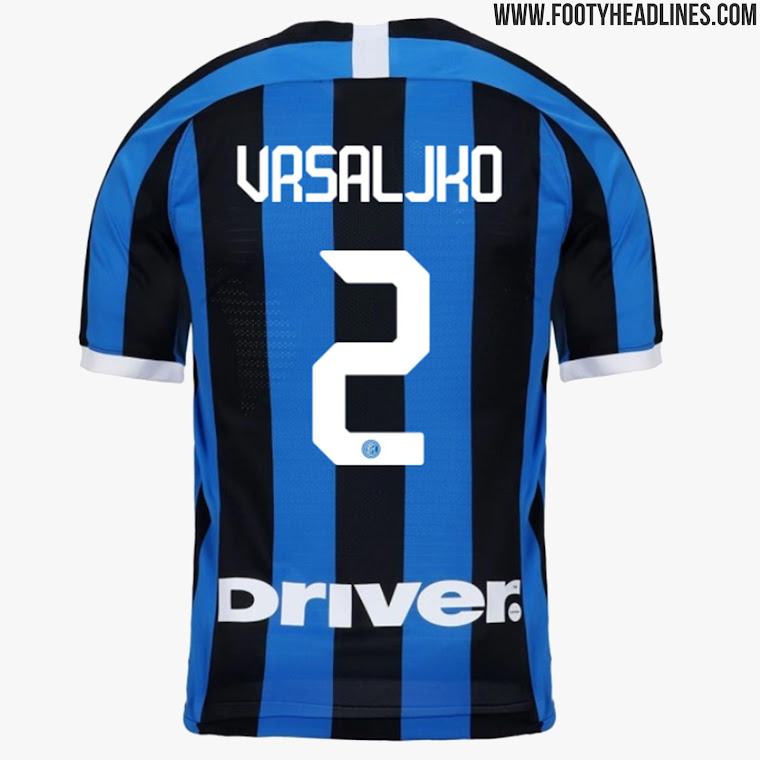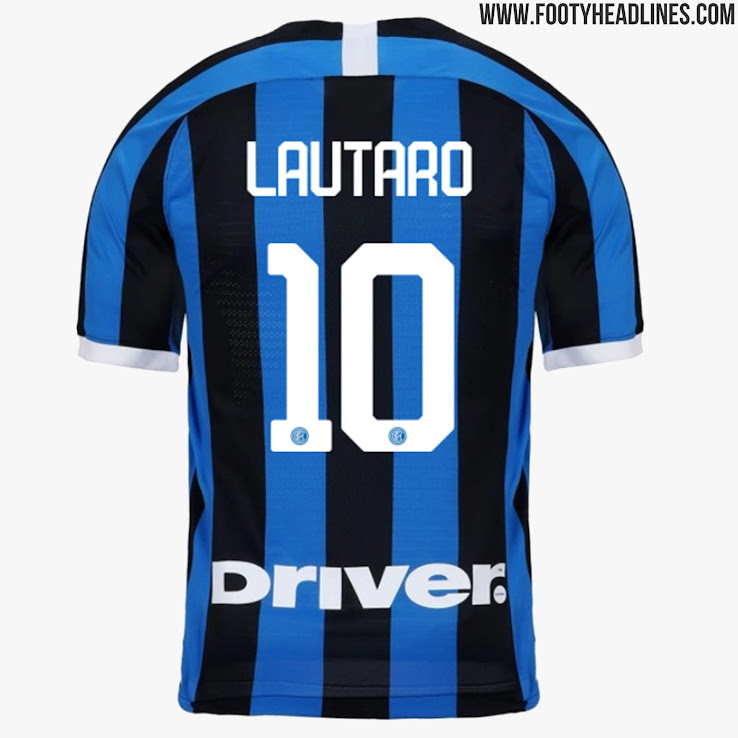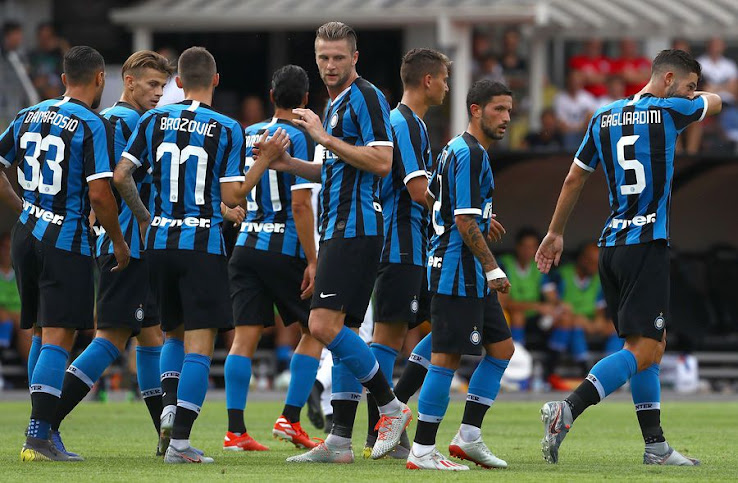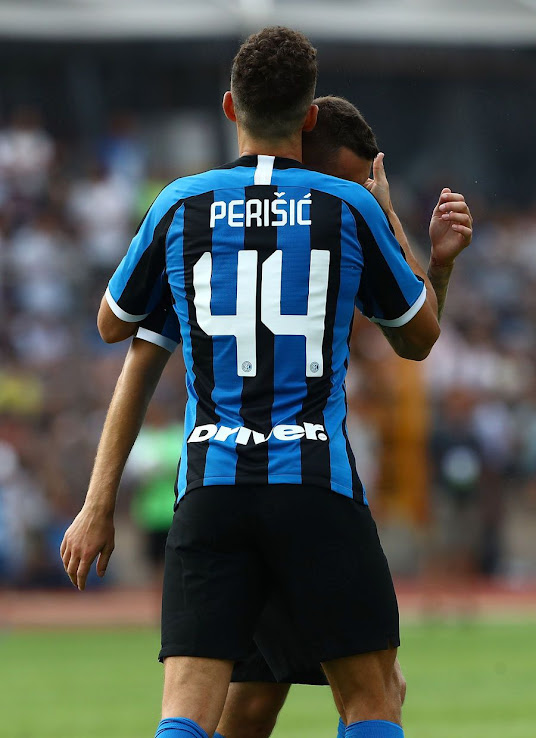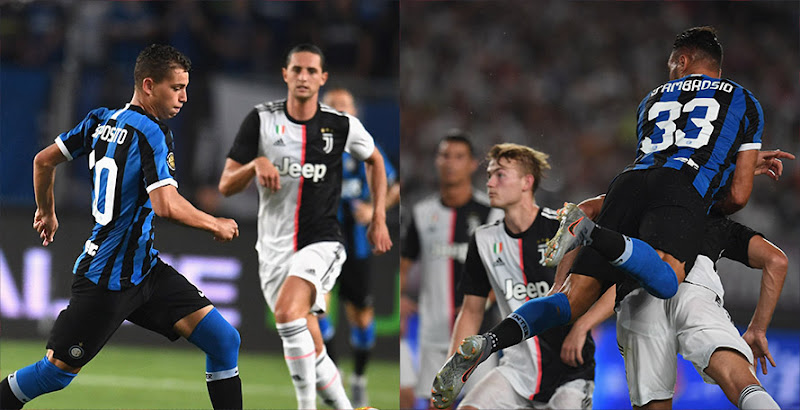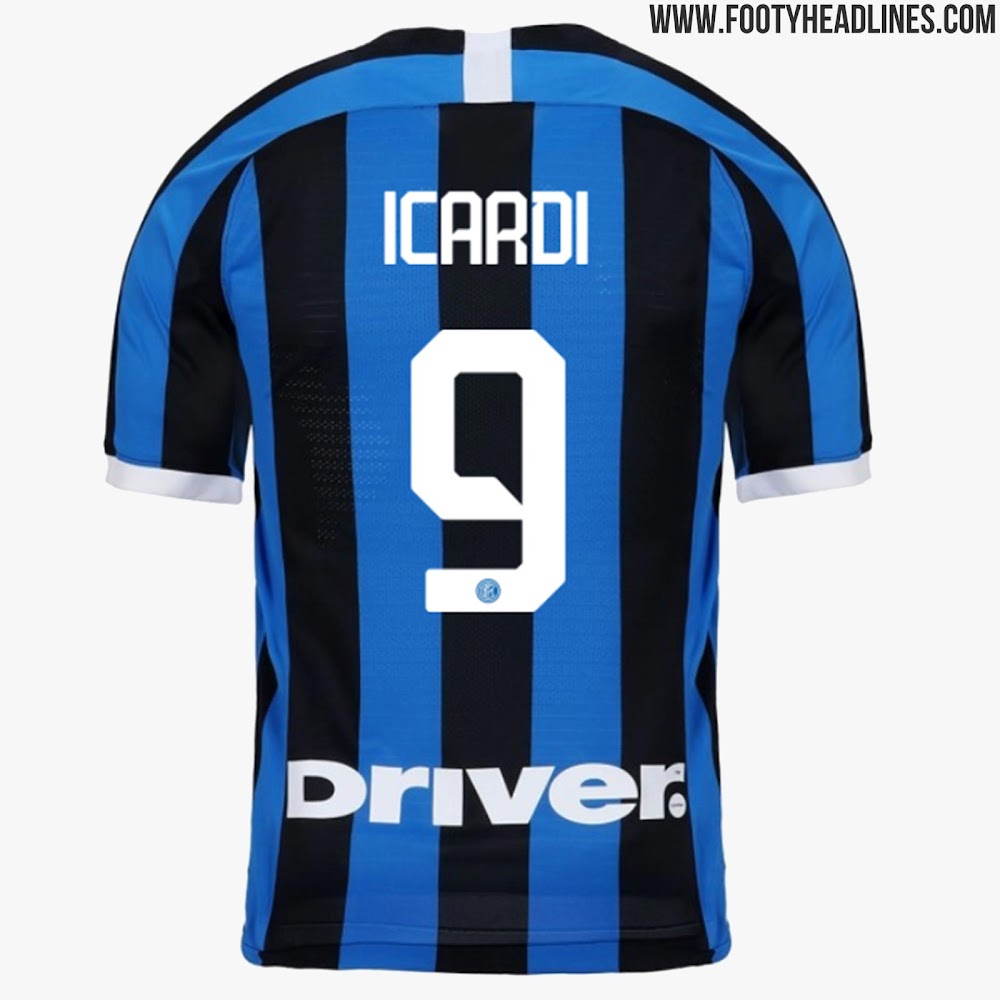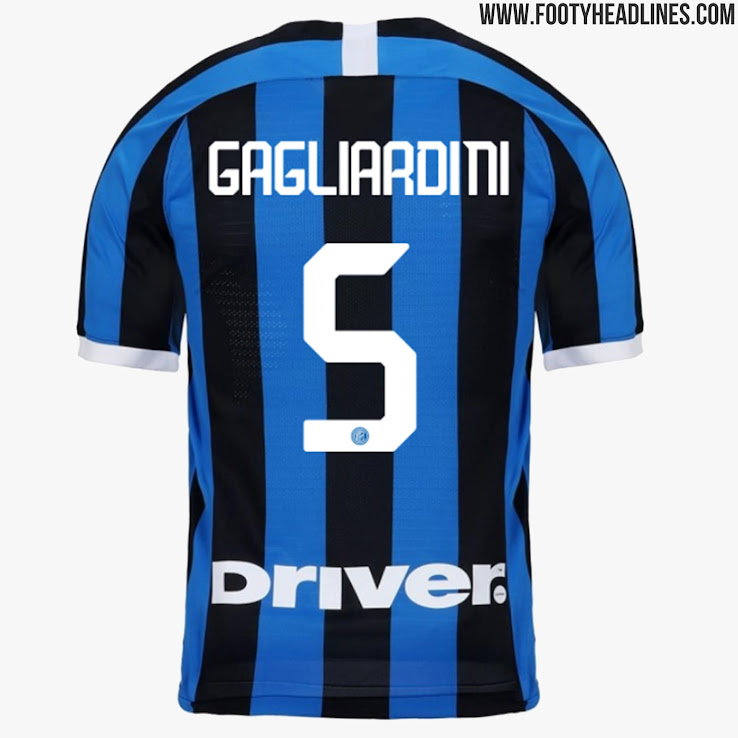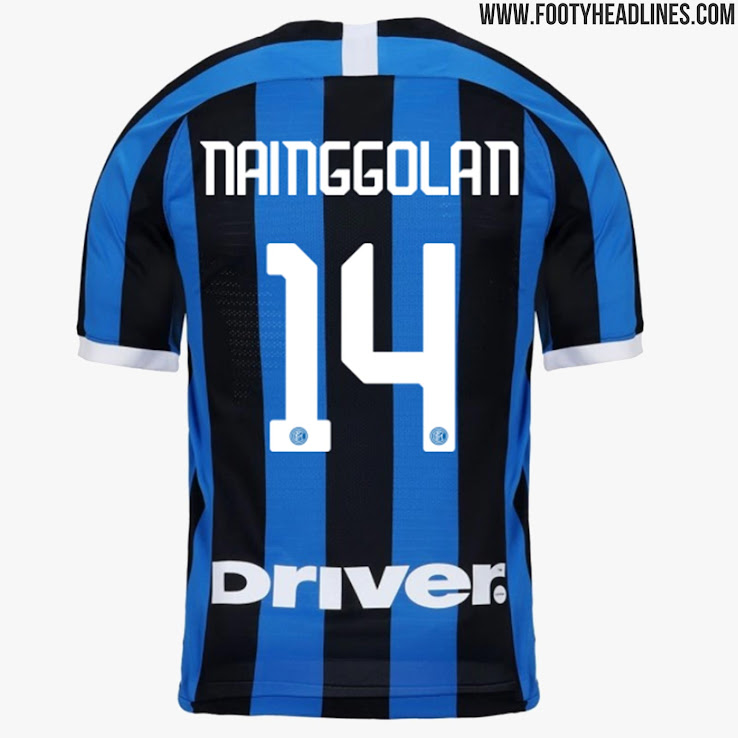
Nike Inter Mailand 19-20 Trikot-Schriftart Veröffentlicht
Update: Inter hat das neue 2019-2020 Heimtrikot im ersten Freundschaftsspiel der Saisonvorbereitung debütiert. Wir haben auch mehr Bilder der Schriftart hinzugefügt (via switchimageproject).
Inter Mailand hat eine neue Schriftart auf den Markt gebracht, die mit den Trikots 2019/2020 verwendet wird. Inter Mailand wird die Schriftart bei allen Wettbewerben in Aktion einsetzen.
Die Nerazzurri werden das neue Trikot mit der Schriftart zum ersten Mal in ihrem letzten Spiel der Saison am Sonntag, den 26. Mai gegen Empoli tragen.
Nike Internazionale 2019-2020 Trikot-Schriftart
Die neue Inter 19-20 Schriftart unterscheidet sich deutlich von der Schriftart der letzten Saison und besticht dennoch durch ein modernes und einzigartiges Design. Die Schriftart wurde von den diagonalen Streifen des Trikots mit einem 45-Grad-Winkel für die Kanten inspiriert.
Schriftart der letzten Saison
„Inter hat eine unglaubliche Heim-Identität, weshalb die Herausforderung gewesen ist, die kultigen Streifen auf moderne und aufbrechende Art und Weise auszuführen, während gleichermaßen die reiche Tradition geachtet wird,“ sagte Pete Hoppins, Nike Football Apparel Senior Design Director. „Wir haben auf die legendären diagonalen Streifen des 1989-Auswärtstrikots zurückgeblickt. Auch das alte Vereinswappen spielte eine Rolle und es führte uns zu diesem sehr klassischen Design - mit einer Wendung in Form der diagonalen Streifen auf der Brust.“
Tatsächlich stellte der Internazionale-Trikotexperte und Designer @rupertalbe fest, dass es sich bei der Schriftart quasi um eine quadratische Version der 2015-2017 Schriftart handelt.